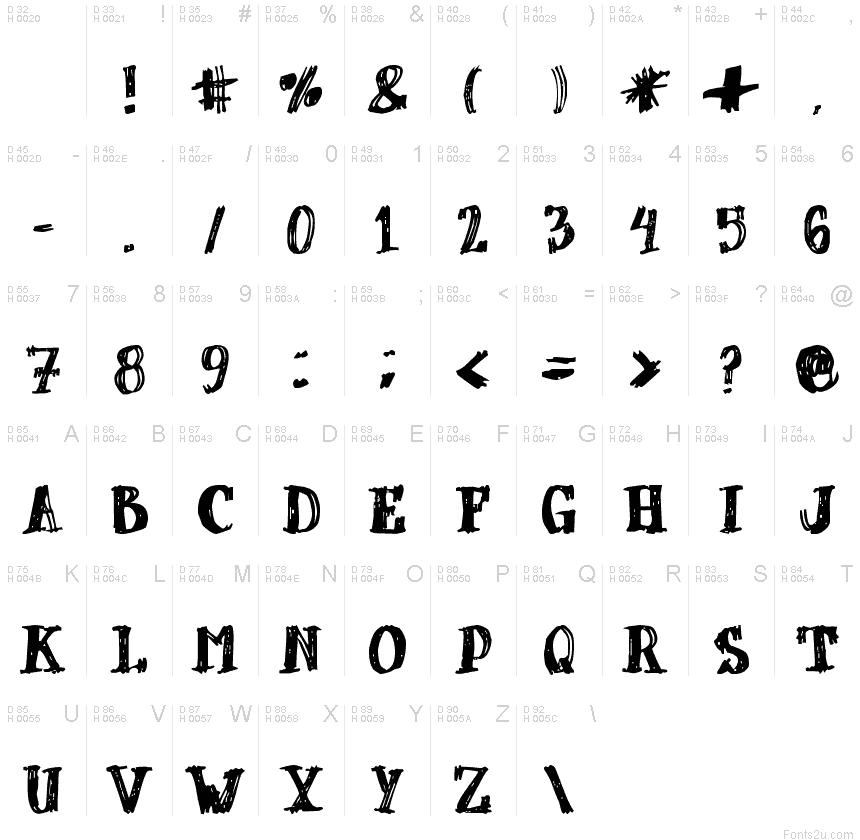
dUBBEL od MillaN to darmowy font w stylu „trash”, który wygląda, jakby został przybity pieczątką, podrapany i przeciągnięty przez mokry atrament. Masywne, nierówne litery zdają się chwiać na linii, pełne dziur i białych drobinek, które przypominają podarty papier lub zerwane plakaty na miejskim murze. Ma w sobie surową, ręcznie robioną energię, która natychmiast przełamuje wszystko, co zbyt czyste lub korporacyjne.
Używając dUBBEL, nadasz ulotkom koncertowym, zinom, tytułom horrorów, opakowaniom DIY, grafikom streetwearowym i śmiałym postom w mediach społecznościowych brudny, zachlapany atramentem charakter. Ten darmowy font najlepiej sprawdza się w większych rozmiarach, gdzie jego chaotyczna tekstura naprawdę może pokazać pazur. Połącz go z prostym, wąskim krojem bezszeryfowym w tekście głównym i pozwól dUBBEL zająć się krzykliwymi nagłówkami i wyrazistymi hasłami.